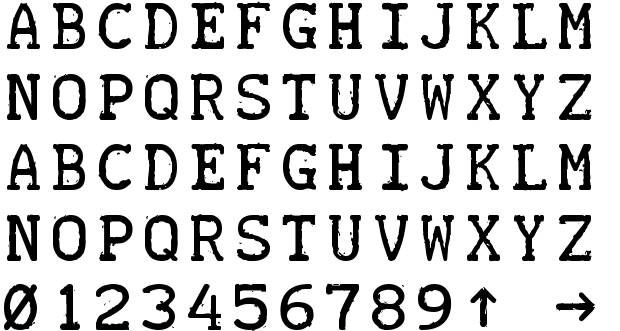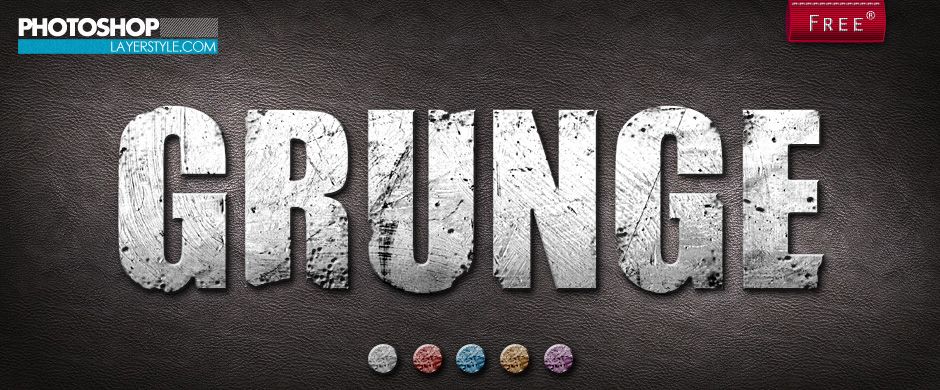
Системы компьютерной графики. Растровая графика. Adobe photoshop. Работа с текстом (модуль 5)
Системы компьютерной графики
Растровая графика
Adobe Photoshop
Работа с текстом
Модуль 5
О чем пойдет речь
Общие сведения.
Создание текста.
Форматирование текста.
Стили текста.
Текст-маска.
Текстовые эффекты.
Общие
сведения
Общие сведения
• Слово шрифт (font) сохранилось еще со времен типографской печати.
• Шрифт включает в себя:
гарнитуру,
размер (кегль),
начертание символов
• Гарнитура (typeface) – набор букв, цифр, символов и знаков препинания
одинаково рисунка.
• Семейство гарнитур (type family) объединяют гарнитуры со специфическими
свойствами.
Семейства гарнитур
Наиболее распространенные семейства:
– Serif
– гарнитура обыкновенная (с засечками).
– Sans-Serif
– рубленная гарнитура (без засечек.)
– Monospaced
– моноширинный, все символы имеют одинаковую ширину.
– Script
– рукописный, гарнитура напоминает рукописный текст.
– Decorative
– декоративный, гарнитура со специальными декоративными
свойствами в виде точек, штрихов и других украшений.
Начертания
Шрифты могут иметь разные начертания (forms).
Начертание определяется:
– насыщенностью
(weight) шрифта
светлый прямой (roman, normal),
полужирный [жирный] (bold)
– шириной (width) шрифта
сжатый (condensed) – шрифт, ширина которого меньше, чем у нормального
аналога,
растянутый (expanded, extended) – шрифт, ширина которого больше, чем у
нормального аналога,
– наклоном шрифта
курсив (italic) – начертание исторически происходит от рукописных текстов,
наклонный (oblique) – более жесткий вариант по сравнению с курсивом.
Размер шрифта определяет высоту символов. Часто используемая единица
измерения – пункт. Один пункт равен 0,35 мм.
Создание
текста
Инструментарий
Графический текст создается с помощью
инструмента Type (Текст) (клавиша T).
Существует два вида этого инструмента:
a. Обычный текст – используется для
добавления надписей в изображение.
a
b. Текст-маска – используется для
b
создания выделений в форме текста.
Если вам необходимо добавить
большое количество текста, в этом
случае удобно пользоваться буфером
обмена для переноса напечатанного
текста из любого текстового
редактора.
Особенности
Текст в Adobe Photoshop это векторное изображение.
В связи с этим есть ряд особенностей работы с ним:
Во-первых, выделять, редактировать текст легко и делается это так, как,
например, в MS Word.
Во-вторых, текст вводится автоматически на новый слой.
В-третьих, если вы захотите применить к тексту фильтры, то надо быть готовыми к
тому, что программа запросит вас разрешение на растрирование этого слоя. А
после растрирования вы должны помнить, что теперь текст ведет себя как
обычное растровое изображение.
Создание текста. Первый способ
1.
Выберите инструмент Type (Текст) (клавиша T)
для горизонтального или вертикального текста.
2.
Щелкните инструментом на изображении –
активизируется указатель ввода текста.
Автоматически появится новый слой.
3.
На панели свойств сделайте нужные настройки
для текста.
4.
Введите нужный текст.
5.
Для завершения процедуры ввода текста на
панели свойств нажмите галочку – Commit any
current edits (b)
В случае, если вы ошибочно начали ввод текста
вам необходимо воспользоваться на панели
свойств кнопкой перечеркнутого круга –
Cancel any current edits (a)
a b
Создание текста. Второй способ
1.
Выберите инструмент Type (Текст) (клавиша T)
для горизонтального или вертикального текста.
2.
На панели свойств сделайте нужные настройки
для текста.
3.
Постройте текущим инструментом
прямоугольную маркерную рамку.
Автоматически появится новый слой.
3.
Введите нужный текст.
Он будет вводится в пределах построенной
прямоугольной рамки.
4.
Для завершения процедуры ввода текста на
панели свойств нажмите галочку – Commit any
current edits (b)
В случае, если вы ошибочно начали ввод
текста вам необходимо воспользоваться на
панели свойств кнопкой перечеркнутого круга –
Cancel any current edits (a)
a b
Отличия
Текст введен первым способом
Текст введен вторым способом
• При вводе текста
вторым способом мы
имеем возможность
регулировать область
расположения текста
с помощью маркерной
рамки, автоматически
появляющейся у
выделенного текста
(см.
рисунок снизу).
Создание текста. Третий способ
Рис. 1
1.
Постройте векторный контур нужной формы
(см. здесь).
2.
Выберите инструмент Type (Текст) (клавиша T) для
горизонтального или вертикального текста.
3.
На панели свойств сделайте нужные настройки для
текста.
4.
Установите курсор в нужное место возле контура пока
курсор не приобретет вид как на рис. 1.
Автоматически появится новый слой.
5.
Введите нужный текст.
Он будет располагаться вдоль векторного контура.
6.
Для завершения процедуры ввода текста на панели
свойств нажмите галочку – Commit any current edits
(b)
В случае, если вы ошибочно начали ввод текста вам
необходимо воспользоваться на панели свойств
кнопкой перечеркнутого круга –
Cancel any current edits (a)
a b
Полезно помнить!
• При вводе текста его
положение можно менять не
закончив операцию ввода
текста.
• Для этого переместите курсор
чуть ниже текста пока он не
приобретет вид как на рисунке
и смело перемещайте текст в
нужное место на изображении
(при нажатой левой клавише
мыши).
Панель «Глифы»
Источник: https://helpx.adobe.com/ru/photoshop/using/glyph-panel.html
Форматирование
текста
Форматирование текста
• Форматировать текст можно как до его ввода, так и после.
• При форматирование текста после его ввода следует помнить, что введенный
текст необходимо для начала выделить, иначе настройки не применятся.
• Выделять символы текста следует при активном инструменте Type (Текст).
• Настройки для форматирования текста можно найти в нескольких местах:
на панели свойств и
на дополнительных палитрах.
Настройки текста. Панель свойств
Изменение
НАПРАВЛЕНИЕ
ТЕКСТА
Определяет
ВЫРАВНИВАНИЕ
строк абзаца
Определяет РАЗМЕР
СИМВОЛОВ (КЕГЛЬ)
ВЫБОР
ГАРНИТУРЫ требуемого набора
символов
Выбор НАЧЕРТАНИЯ –
определяет
насыщенность и объем
Определяет СГЛАЖИВАНИЕ
символов текста, т.е.
позволяет сглаживать
зубцеобразные края текста
Выбор
ЦВЕТА
символов
текста
Получение
ДОПОЛНИТЕЛЬНЫЕ
ПАЛИТРЫ НАСТРОЕК
ТЕКСТА
ИСКАЖЕНИЕ
ТЕКСТА –
позволяет
расположить
текст в
векторной
рамке
произвольной
формы
ОТМЕНА
ВВОДА
текста
ПОДТВЕРЖДЕНИЕ
ВВОДА текста
Дополнительные палитры настройки текста
Настройки символов текста
Выбор гарнитуры
Размер символов текста
Кернинг – расстояние как между
отдельными символами
Задает коэффициент масштабирования
символов по высоте
Задает смещение
базовой линии текста
Выбор начертания
Интерлиньяж – вертикальное
расстояние между строками текста
Трекинг –расстояние как между
словами, так и символами
Задает коэффициент масштабирования
символов по ширине
Выбор цвета символов текста
Выбор начертания
Определяет словарь
для переносов
Определяет вид
сглаживания
Настройки абзацев текста
Выбор способа выравнивания
строк абзаца
Отступ абзаца слева
Отступ абзаца справа
Величина абзацного отступа
Интервал перед абзацем
Включение переносов
Интервал после абзаца
Палитра Properties (Параметров)
Настройки текста
Расширенные настройки текста для
шрифтов OpenType
Получение
ДОПОЛНИТЕЛЬНЫХ ПАЛИТР
НАСТРОЕК СИМВОЛОВ
ТЕКСТА И АБЗАЦА
Работа со шрифтами
Поиск шрифтов
Для поиска шрифта достаточно ввести
несколько букв его названия в окно
выбора, Photoshop отобразит все
шрифты, имеющие в названии эту
комбинацию букв.
Также для поиска можно использовать
фильтр (см. рис. справа).
Предварительный просмотр
шрифтов
Есть возможность удобно
посмотреть, как будет смотреться
тот или иной шрифт в документе.
Сделав активный текстовый слой,
открыть список и перемещать
курсор по списку без нажатия на
клавишу мыши. Шрифт в
документе при этом не меняется
пока вы не выберите нужный вам
шрифт
Работа со шрифтами из Typekit
Подробнее читайте здесь: https://helpx.adobe.com/ru/photoshop/using/fonts-typekit.html
Новинка: Переменные шрифты OpenType
• Шрифт OpenType
поддерживает такие
настраиваемые
атрибуты, как толщина,
ширина, наклон,
оптический размер и т. д.
• Photoshop поставляется с
несколькими переменными
шрифтами, для которых можно
регулировать толщину, ширину
и наклон с помощью
стандартных ползунков на
панели «Свойства».
• На панели «Символ» или
панели «Параметры» введите
поисковый запрос
«переменный» в списке
шрифтов для поиска
переменных шрифтов.
Также
можно щелкнуть значок рядом
с именем шрифта.
Источник: https://helpx.adobe.com/ru/photoshop/using/fonts.html
Команды работы с текстом
Растрирование текстовых слоев
Первый способ
Растрирование текстовых слоев
Второй способ
Важно!
Вид макета на
другом ПК –
шрифты не
растрированы,
на ПК нет
нужных шрифтов
Макет на
вашем ПК
http://manjuna.com/tutorial-web-design/
Перед просмотре изображения на другом ПК полезно текстовые слои растрировать, оставляя у
себя вариант в векторе, чтобы оставить возможность дальнейшего редактирования.
Это делается для того, чтобы в случае, если на другом ПК не загружены нужные шрифты
дизайн-макет отображался корректно.
В случае, если текст будет оставаться в векторном представлении, а на ПК не будут загружены
нужные шрифты при открытии документа программа выдаст предупреждения и загрузить текст
с другими шрифтами. Это может привести к некорректному отображению дизайна.
Автоматическая вставка текстовых заглушек
Задание. Создание портрета из текста
Создать портрет из текста.
портрет.jpg
До
После
Задание. Создание портрета из текста
1.
2.
1
Открыть портрет, на основе которого сделаем портрет из
текста (portrait.jpg).
Построить выделение портрета с помощью команды Color
Range (Select/Color Range).
4
5 Select/Color Range
6
2
10
7
3
8
9
3.
4.
Создать новый слой (Layer 1) и залить выделение черным
цветом.
Снять выделение.
Задание. Создание портрета из текста
5.
6.
Создать текстовую заглушку размером с документ
(см. рис. слева).
Загрузить выделение (Ctrl + кликнуть по миниатюрке
слоя Layer 1) (см. рис. Справа).
Задание. Создание портрета из текста
7.
8.
9.
Создать маску слоя с текстовой заглушкой (см. рис.
слева).
Снять выделение.
Создать новый слой (Layer 2) под текстовым слоем и
залить его белым цветом.
(см. рис. справа).
Задание. Создание портрета из текста
8. Сравните результат.
Стили
текста
Зачем нужны стили текста?
• Для соблюдения текстового единообразия в
подготовки изображений одного проекта, при работе с
большим количеством текстовых слоев и др. можно
автоматизировать работу, используя стили текста.
• Различают стили символов и стили абзацев.
Стили символов
Стиль символа включает в себя атрибуты форматирования
символов к символам, абзацу или даже к нескольким абзацам.
Можно создать стили символа, а затем применить их позднее.
Выберите Window > Character Styles, чтобы открыть палитру
«Стили символов». Чтобы применить стиль символа, выделите
текст или текстовый слой и щелкните стиль символа.
Стили шрифтов являются иерархическими: параметры, указанные
вручную, переопределяют любые примененные стили символов,
которые в свою очередь заменяют примененные стили абзацев.
Этот иерархический подход объединяет эффективность
использования стилей и гибкость при настройке проектов.
Подробнее изучить:
• Создание стиля символа.
• Редактирование стиля символа.
• Определение стилей шрифтов по умолчанию.
См. здесь: https://helpx.adobe.com/ru/photoshop/using/formatting-characters.html#main-pars_header_3
Стили абзаца и символов
Стиль абзаца включает в себя атрибуты форматирования как
символов, так и абзацев и может быть применен к одному или
нескольким абзацам. Можно создать стили абзаца и затем
применить их позже.
Выберите Window > Pharagraph Styles, чтобы открыть палитру
«Стили абзацев». По умолчанию каждый вновь созданный
документ содержит стиль «Основной абзац», который
автоматически применяется к вводимому тексту. Этот стиль
можно изменить, но переименовать или удалить нельзя. Стили,
созданные пользователем, можно переименовывать и удалять.
Можно также выбрать другой стиль в качестве стиля,
применяемого к тексту по умолчанию.
Чтобы применить стиль абзаца, выделите текст или текстовый
слой и щелкните стиль абзаца.
Стили шрифтов являются иерархическими: параметры, указанные
вручную, переопределяют любые примененные стили символов,
которые в свою очередь заменяют примененные стили абзацев.
Этот иерархический подход объединяет эффективность
использования стилей и гибкость при настройке проектов.
Редактирование стилей абзаца
Двойной клик
Подробнее изучить: https://helpx.adobe.com/ru/photoshop/using/formatting-paragraphs.html#main-pars_header
Важно!
• При создании нового документа для
проекта начинайте с создания стилей для
символов и абзацев текста.
• Например, полезно задавать стили для:
–
Заголовков.
Подзаголовков.
Основного текста.
Подписей.
Гиперссылок.
И т.п.
Текст-маска
Работа по созданию и форматированию текста-маски
идентична работе с обычным текстом.
Пример
1.
2.
3.
4.
Выберите инструмент Horizontal
Type Mask.
Настройте параметры текста:
кегль (размер) – 160рt
шрифт – Verdana
начертание – Bold
Кликните на изображении и
введите слово «Фрукты»
заглавными буквами (должно
получиться как на верхнем
рисунке).
Завершите ввод текста Commit
any current edits.
Получатся выделения в форме
букв (см. средний рисунок)
Этот инструмент хорошо использовать
для создания маски слоя (см. нижний
рисунок), для вырезания изображения в
виде букв текста и т.п.
Текстовые
эффекты
Текстовые эффекты
Текстовых эффектов можно добиться с помощью:
1. Применения к тексту настроек форматирования.
2. Применения к слою с текстом эффекта слоя.
3. Применения к слою с текстом фильтров.
Применение настроек форматирования
Буквица
Это будет не буквица как таковая, а ее имитация.
В этом случае достаточно увеличить первую букву в слове
В случае, если вы хотите сделать не имитацию, а настоящую буквицу, то
увеличить букву мало, следует сместить положение ее базовой линии
вниз
«Пляшущий» текст
В этом случае последовательно выделяя каждую букву слова, измените
ей смещение по базовой линии текста: для первой буквы сделайте
положительное смещение, для следующей – отрицательное и т.
д.
Фигурный текст
В этом случае, воспользуйтесь с панели свойств инструментом
искажения текста, который позволит вам расположить текст в векторной
рамке произвольной формы. Например, сделать слово «рыба» в форме
рыбы и т.п.
Вы можете, экспериментируя, продолжить этот список и прислать
преподавателю, как дополнительный бонус к домашнему заданию
Применение эффекта слоя для текстовых эффектов
Чтобы получить представление каким образом создаются
текстовые эффекты с помощью эффектов слоя проделайте
урок «Отливаем текст из золота в Фотошоп»:
https://photoshop-master.ru/lessons/text/otlivaem-tekst-iz-zolota-v-fotoshop.html
Применение фильтров для текстовых эффектов
Однако, на практике редко используют только фильтры или
только эффекты слоя, поэтому часто для достижения
разнообразных текстовых «красивостей» применяют
комбинацию всех возможных способов создания текстовых
эффектов.
Проделайте еще один урок по созданию золотых букв, в котором
эффект достигается уже не только эффектами слоя, но и
фильтрами.
Урок «Пишем золотыми буквами в Фотошоп»:
https://photoshop-master.ru/lessons/text/pishem-zolotyimi-bukvami-v-fotoshop.html?download=e59522068f3f0aec4d537d579556ec02
Задание
• Возьмите любое изображение.
• Повторите все имеющиеся на данном примере текстовые
эффекты данного плаката.
Обязательно к изучению!
• В приложениях к модулю 5 вы расширите свои знания
по работе со стилями слоев и фильтрами.
Спасибо
за внимание!
Твои вопросы?
Ты можешь их задать:
На форуме «Вопросы по курсу»
56
Ликбез онлайн-версии фотошопа. Шрифты и изготовление быстрой визитки
Этот мастер-класс в помощь тем, кто не умеет работать в фотошопах и аналогичных программах. Или имеет только поверхостное ознакомление с ними. Мы разберем все инструменты онлайн-версии фотошопа, которую не нужно ни скачивать, ни устанавливать. Расскажу, где искать и как устанавливать красивые русскоязычные шрифты. Я открою пару интересных секретов быстрой обработки изображения.
И расскажу, как быстро сделать визитку и подготовить ее к печати дома.
Я заметила, что на Ярмарке Мастеров очень много мастеров, не имеющих опыта работы в фотошопе. Программа дорогая, не все могут ее себе позволить. Кроме цены – она также весьма сложная и разобраться без специальных мастер-классов в ней тяжело. Хочу немного помочь всем тем, кому нужно делать бирочки, визиточки, баннеры или просто подпись к фотографии – это легко и просто делается без скачивания спец-программ. Мы будем использовать так называемый фотошоп-онлайн. Внимание! Нам нужен будет фотошоп с такой заставкой вначале:
Нашли? Отлично! Пока мы не начали работать – давайте подберем какие-нибудь интересные шрифты! Именно подбор шрифтов – главная проблема для многих. Во-первых, где их брать? Во-вторых – как устанавливать? Все очень просто. Шрифты находятся в интернете. В поисковик забиваем «шрифты скачать». Сайтов очень много. Как выбрать среди них?
Критерии первый: должна быть возможность как-то выбрать просмотр только кириллических или русских шрифтов.
Везде их называют по-разному. Суть в том, чтобы нам показали максимальный выбор шрифтов с русской раскладкой. Конечно, это актуально в том случае, если визитки, бирочки или баннер вы хотите заполнять на русском языке. Если вам нужны латинские шрифты – все просто. Качать можно любой понравившийся – 90% шрифтов именно англоязычные.
Вы смогли отрегулировать фильтр поиска или же там просто русские шрифты выделены отдельной категорией. Заходим. Вы увидите название шрифтов, под ним картинка – название шрифта, написанное самим шрифтом. Шрифтов сотни и тысячи. Не стоит пытаться скачать все. Выбирайте те, что нравятся. Безусловно, всегда полезны рукописные; “bold”, т.е. жирные; различные “old”, т.е. под старину; готические и прочие. Часто, принадлежность к какой-либо категории у шрифта написана в названии. Вы часто можете увидеть один и тот же шрифт, который сначала идет отдельно bold, потом italic (курсив), затем bold italic. Почему так? Ведь мы привыкли, что выбираешь шрифт, а потом отдельной кнопкой делаешь его жирным, курсивом или прочее.
У нестандартных шрифтов такой возможности нет. Если шрифт состоит из тонких букв – таким он и останется. И толстые буквы будут только, если вы скачаете отдельный такой же шрифт с подписью bold. Есть еще варианты, когда буквы прозрачные, т.е. есть только их контур, или же заполнены некоторым узором, а не просто черные. В общем, полистайте, посмотрите – это ужасно интересно. Руки так и тянутся все скачать 🙂
Теперь второй критерий: возможность посмотреть шрифт до скачивания! Обычно есть кнопка «посмотреть шрифт» или «весь шрифт». Или при нажатии на шрифт – он открывается в окне и там будет его раскладка. Выглядит это так:
Зачем это нужно? Дело в том, что, даже когда вы выбираете только кириллические или русские шрифты… все равно среди них как минимум половина будет без русской раскладки! Теперь как разобраться в таблице букв. Сначала идут латинские буквы – большие и маленькие. Потом цифры, затем значки… и только после этого идет русская раскладка – также больших и маленьких букв.
Если на русской раскладке вместо букв пустые окошки или черные квадратики – у этого шрифта нет русской раскладки! Бывает, что у шрифта есть только большие или только маленькие буквы. Конечно, лучше всего, если присутствуют все буквы – и большие, и маленькие. Но это не обязательно. Наличие знаков – тоже желательно. Хотя бы та же @ — нужна нам для того, чтобы написать в визитке почту. Но, если шрифт вам очень нравится, а «собачки» там нет – не расстраивайтесь – найдете этот значок в другом шрифте, хотя бы в том же стандартном.
И так. Шрифты накачали. Установить их очень просто. Если у вас старая версия оперативной системы, то Мой компьютер-Windows-Fonts. Распаковываем шрифты из архива, если они были в архиве. Переносив шрифты туда без папок! Прямо в корень. Он их начнет устанавливать после этого сам. Если у вас новая оперативная система (хотя бы семерка) – тогда просто щелкните два раза на каждой файле шрифта – и он начнет устанавливаться сам. Шрифты тогда появятся у вас в ворде, фотошопе и также онлайн его версии (все программы желательно открыть заново после установки шрифтов).
Теперь можно приступать к изучению фотошопа-онлайн.
Сначала ликбез. Разберем окно, которое открывается при старте.
1. Создать новый рисунок. При открытии появляется окно. Первая строка — «имя» — можно не вводить. Затем — «предварительные настройки» — тут есть некоторое количество стандартных форматов, которые можно выбрать. Если вы не хотите стандартный размер изображения – выбираете его сами, выставив ширину и высоту ниже. К сожалению, выбор только в пикселях, разрешение выставлять нельзя! Если хотите разрешение побольше – лучше найти как-то файл с изображением в интернете и открыть его в фотошопе. Какая картинка не важна – сверху нарисовать можно что угодно) Главное, получить файл с изначально высоким разрешением.
2. Загрузить изображение с компьютера. Тут все понятно. Кушает он достаточно много форматов, в том числе, и psd – формат, сохраняющий слои.
3. Можно открыть файл сразу из интернета.
Когда нашли в интернете понравившуюся картинку, ее можно не скачивать, а нажать правую кнопку мыши и выбрать «копировать адрес изображения».
4. Открыть изображение из библиотеки – т.е. из всяких соцсетей.
5. Последнее – открыть с телефона.
Мы создали или открыли файл. У нас есть горизонтальные вкладки и вертикально расположенные окна инструментов.
Горизонтальное меню (сверху):
Файл: понятно — тут открываем, сохраняем и прочее.
Редактировать: тут инструменты для выделения, поворота, копирования и вставки. В какой-то степени, они дублируют основные инструменты, которые находятся на вертикальной панели слева. Редактирование – Free transport – это возможность повернуть или отразить рисунок, а также уменьшить. Действует только на слой! Чтобы пропорции изображения не менялись – зажмите shift. Чтобы отразить рисунок – зажмите правую кнопку на уголке и переместите ее слева направо, чтобы отразить горизонтально и сверху вниз, чтобы вертикально.
Только shift не зажимайте. Если зажать shift – изображение повернется, будто вы его просто повернули верх ногами 🙂
Изображение: тут можно переворачивать наш файл. Именно файл! Файл состоит из нескольких слоев – переворачиваться будут все слои. Тут же есть отразить по вертикали или горизонтали, также можно менять размер файла.
Слои: меню по работе со слоями. Почти все, что там есть – дублируется другими инструментами.
Коррекция и фильтр: обработка фотографий. Свет, яркость, цветность, различные деформации, формы и прочее. Честно говоря, там надо каждому самому покопаться. Вместить сюда курс коррекции фотографии и использования фильтров… лучше отдельным постом, хотя тут и так постов на эту тему много. Тут есть даже такие фильтры… которых в фотошопе нет! Например, калейдоскоп 🙂 А еще есть инструмент «придание точечного стиля» – из любого рисунка можно сделать схему для вышивки!
Просмотр: тут есть возможность открывать разные окна, которые очень нужны.
Окна горизонтальных дополнительных инструментов, навигатор (чтобы приближать), слои (те самые!), журнал (она же история, чтобы можно было вернуться назад – ужасно полезно! Журнал свой для каждого открытого файла.
Язык и помощь – тут тоже все ясно 🙂
Рассмотрим левое вертикальное окно. Условно инструменты можно поделить на инструменты для выделения, рисования и коррекции. Рассмотрим первый блок.
Когда вы жмете на одну из кнопок инструмента – в горизонтальном окне сверху появляются доп. функции (на сером фоне).
Обрезка – инструмент, позволяющий не только обрезать, но и контролировать размер обрезки края. Тут все ясно – тыкаем на инструмент, обрезаем картинку по краю, например. Если сверху на серой полосе у нас стоит в окне «без ограничений» — то можно просто обрезать изображение так, как хочется. Если нам нужно сохранить соотношение сторон (по соотношению сторон открытого файла) – например, для того, чтобы потом напечатать фотографию для альбома – то вбираем «соотношение сторон».
По умолчанию стоит 1:1 – т.е. с сохранение пропорций сторон. Если нам нужно задать какой-то определенный размер, то выбираем «выходной размер», ставим нужное количество пикселей по вертикали или горизонтали. Это удобно, например, для создания аватарок. Выставлять все параметры нужно до того, как вы начали обрезку файла!
Выделение – все логично. Что-то выделяем, затем, чтобы переместить выделение, не вырезая картинку, просто жмем на выделенный участок, а чтобы вырезать и использовать выделенное где-то еще, его можно перетащить с помощью инструмента «перемещение». Пробежимся по дополнительным функциям. Значит, два вида выделения: прямоугольное или в форме эллипса. Ограничение – тоже, что в инструменте «обрезка». Растушевывание – это возможность сделать край при выделении не резким, а растушеванным. Эффект от инструмента «в форме эллипса» показан на первой картинке, а от инструмента «прямоугольное выделение» на второй картинке. Здесь края прямоугольника за счет растушевывания можно красиво сгладить.
На примере размер растушевывания =17. Но это все зависит от начального разрешения файла.
Перемещение – нужен в работе со слоями, о которых я расскажу позже. С помощью него можно перемещать объект на слое по нашей картинке и перемещать слои в других файлы.
Лассо – это также инструмент выделения, но более тонкого, чем простое выделение. На мой взгляд свободное лассо вообще бесполезно. Гораздо удобнее многоугольное лассо. С помощью него можно очень точно выделить любой объект. Чтобы край был не резкий, можно даже немного растушевать. Чтобы вырезать объект, сначала его приближаем (инструмент «навигатор» справа). Затем левой кнопкой мыши идем вдоль края, отмечая как бы точки перегиба лассо там, где наша линия меняет направление. Этот же инструмент есть и в нормальном фотошопе. Там им пользоваться очень удобно, а вот в онлайн-версии много глюков. Во-первых, чтобы удобнее вырезать по линии объект – его нужно приблизить, а, значит, объект не влезет весь на экран и его нужно передвигать.
А в онлайн версии сдвинуть окно нельзя во время выделения. Точнее можно, но, почему-то, выделенная вами область тут же смещается вслед за окном. Короче, неудобно! Ниже, в МК по созданию визитки я поподробнее расскажу, как вырезать, также используя дополнительно инструмент «волшебная палочка».
Волшебная палочка – это автоматическое лассо. Не пользуйтесь этим инструментом, если хотите аккуратный результат. Пользовать им можно только на очень контрастных изображениях. Хорошо на черно-белых. Но граница все равно будет неровной. Это убыстряет процесс, но только если нет градиента цветов – а он есть почти всегда. Использовать ее можно только в комплексе с другими инструментами выделения. Внизу, на мастер-классе визитки я это покажу.
Второй блок инструментов:
Карандаш и кисть – инструменты рисования. Честно говоря, эти инструменты чаще используют те, у кого есть планшет и те, кто умеет рисовать. Это особенно относится к карандашу.
Не понимаю, что с ним делать. А вот «кисть» очень полезный инструмент. Заходим в меню кистей.
Сверху появляется дополнительные иконки – чтобы открыть меню выбора кистей нужно нажать на изображение кисти рядом со словом «кисть:». Там вы видите стандартный набор кистей. Можно достаточно интересным методом создать свою кисть – выбрать круглой она будет или квадратной, какой нажим, где разрезы в контуре и прочее. Но давайте научимся использовать уже готовые кисти.
Кроме стандартного набора тут есть некоторый набор, который можно загрузить из архива программы. Нажимаем кнопку «другие параметры». Там потыкайтесь – есть штук 20 разных наборов кистей, вполне даже приличных. Чтобы они добавились – жмем добавить. Для меня оказалось абсолютной неожиданностью, что функция загрузить кисти с компьютера тут есть… вот только стандартный тип файла кистей .abr он не видит. И требует какой-то непонятный .pbr! Что за невидаль? Сунулась в интернет. Все кисти только в формате .abr! И люди, задающих один и тот же вопрос – где взять кисти в странном формате .
pbr? Попробовала взять кисти из своего нормального фотошопа и сохранить в странном формате, но фотошоп отказался. Интернет ищет только кисти формата .abr. Это ужасно печально, так как выбор стандартных кистей из тех, что он подгружает из своего архива, невелик. Нет красивых завитушек, мало растительного орнамента… Ну, что поделать. Но, если вы используйете фотошоп или его бесплатный аналог, то использовать кисти нужно. Для этого – вводим в поисковик «кисти для фотошопа». Обычно рядом с кистями есть и инструкция по их установке. Для каждой программы по-разному.
Ладно, вернемся к другим функциям кистей. Вот вы загрузили разные кисти из архива. Можно менять их размер. Делать кисть прозрачнее. Есть также функции Hard tip – т.е. резкий край, диффузия – рассеивает узор кисти. А инструмент «рассеять» – актуален только если вы хотите изобразить летящие листья или рассеянные звезды. Т.е. жмешь несколько раз – а листья появляются не в том месте, где нажимаешь, а в случайном месте. В большом открывающемся меню еще есть три параметра – диаметр, регуляция той самой рассеивания – расстояния между рассеянными объектами и твердость.
Ластик – тут все ясно. Можно стирать уже нарисованное. Удобно, что ластик действует на слой. Т.е. можно нарисовать что-то на отдельном слое – и, если потребуется стирать, стирать будем на отдельном слое. Я постаралась показать. На мишку я наложила другой слой и легко смогла с него стирать, не затрагивая мишку. Также можно и рисовать. Кстати, край ластика тоже можно рассеивать. Формы ластика – это те же формы, которые мы загружали в кисти.
Заливка – ну… это возможность заливать что-то цветом. Честно говоря, удобна только для заливки основного фона. Действует на слой.
Градиент – это та же заливка, только красивым градиентом. Инструмент работает так: левой кнопкой мыши отмечаем начальную точку, не отпуская кнопку, тянем в одну из сторон – чем дольше тянем – тем более растянутый будет градиент. Можно тянуть по горизонтали, можно по диагонали. Есть стандартные градиенты, можно создать самому. Для этого на горизонтальной шкале градиента нажмите в любом месте – появится зарубка.
Каждую такую зарубку можно двигать, менять ее цветность и непрозрачность. Там же можно делать линейный градиент, радиальный, с повторами и прочее… Активная зарубка обозначена черным треугольником сверху. Я ее отметила красным. Я убрала прозрачность – и в этом месте градиента стал виден нижний слой с мишкой.
Штамп – очень интересный инструмент коррекции. Наведите курсор на то место, которое хотите «запомнить», нажмите ctrl – курсор поменяет форму на крест – и нажмите левую кнопку мыши. Чтобы текстуры лучше ложились в новое место – лучше использовать кисть с растушеванным краем. Затем переносите объект в другое место. Таким нехитрым инструментом я сделала мишке лишний десяток глаз… Но чаще всего инструмент применяют для коррекции дефектов кожи или же обрезанного края, который нужно дорисовать.
Рисование – это инструмент рисования прямоугольников, кругов и линий. Опять же можно сделать их прозрачными, можно добавить границу. Внутренняя часть фигуры будет заполнена тем цветом, что указан в горизонтальном меню справа, а цвет границы, если ее поставить хотя в 1 пикель, цветом, который указан слева внизу.
Дальше идут инструменты важные скорее для обработки фотографий.
Размытие и резкость – тут все ясно. Делаем что-то размытым или резким. Причем можно регулировать интенсивность и форму кисти.
Палец и губка – это странные инструменты. Некоторые люди используют палец для размытия дефектов. Губка – это что-то странное. Представьте, что у вас есть рисунок акварелью – и вы на него капнули водой и начали по нему возить губкой. Вот что-то такое…
Осветление и затемнение – все для работы с фотографиями.
Красные глаза – понятно, убирает красные глаза.
Точечная коррекция – это интересные инструмент для редактирования фотографий. Убрать родинку или прыщик? Нажали и готово! Даже лучше пальца) Штамп – это примерно тоже самое, но коррекция более автоматически сливает текстуры. А штамп просто накладывает изображение сверху.
Раздувание и дисторсия – это такое веселый инструмент, которым можно делать смешные рожицы с большими глазами или подправлять фигуру 🙂
Пипетка очень полезна – наводите на нужный цвет – и вот он в палитре…
А – это текст.
Как раз тут множество шрифтов, которые мы себе установили. Можно менять размер, можно менять жирность (это называется стиль), курсив и прочее (в других редакторах так нельзя, только тут уже жирный шрифт можно сделать еще жирнее, а курсив… еще более наклонным :)), поменять цвет. Шрифт выбираем из тех, что установили себе на компьютер – программа использует шрифты с вашего компьютера. Шрифт всегда печатается на новом прозрачном (!!!) слое. Так что вы легко сделаете подпись к вашей фотографии.
Палитра! Тут не все так просто. Она тут аж в 4-х варианта. HSL, RGB, WEB и IMG.
IMG – это фактически не палитра. При открытии файла – программа считывает все цвета, которые в ней есть и отражает их.
WEB – это стандартная палитра, закомая вам по ворду. Она достаточно ограничена в цветах.
RGB – тут вы видите три круга с пересечением. Внизу линии – они меняют цветность каждого круга. От этого меняется цвет в центре пересечения трех кругов.
HSL – тут немного сложнее. Верхняя горизонтальная линия двигает кружок по цветовой окружности. Средняя – отвечает за интенсивность от белого до яркого цвета, нижняя – тоже от черного до яркого цвета. За счет этих двух линий кружок бегает по ромбу внутри окружности. Кроме того, за счет линейки дополнительных цветов в палитре справа можно к любому выбранному цвету сразу увидеть несколько близких тонов. Еще интересно. У каждого цвета есть свой номер. Это в том случае, когда вам нужно точно сохранить оттенок – можно просто ввести его номер.
Теперь о слоях. Это самое важное в фотошопе.
Если вы когда-то открывали Paint, то заметили, что там ты рисуешь всегда на одном и том же слое. Если что-то нарисовал – там оно и остается – ни сдвинуть, ни стереть, не повредив другую часть рисунка. А вот в фотошопах и его аналогах можно. Слой можно представить себе прозрачной пленкой. Вы можете нарисовать на каждом слое пленки разное, а потом легко двигать их между собой, при этом общая картина будет меняться.
При этом слой можно сделать невидимым, если он вдруг вам мешает прямо сейчас. Слои можно менять местами. Всегда создавайте новый слой, когда собираетесь что-то рисовать. Когда создаете текст – слой создается автоматически, называется текстовым и отмечен буквой «А» в меню слоев. На текстовом слое нельзя рисовать, редактировать его можно ограниченно. Зато можно менять в любой момент шрифт и его цвет. Текстовый слой можно растрировать – т.е. превратить в растровый. Тогда менять шрифт уже будет нельзя, буквы на слое будут простым изображением, как и любой другой рисунок. Зато можно уже его редактировать всеми инструментами программы. Далее… не забывайте! Если вы рисуете что-то сами кистью – обязательно создавайте новый слой. Так как именно на слой направлено действие всех инструментов фотошопа. Если вы нарисуете что-то просто на слое с изображением и захотите потом что-нибудь стереть – не получится. Новая часть рисунка будет стираться вместе с изображением.
Как создать слой?
Красной стрелкой я отметила кнопочку.
Новый слой будет виден в меню справа весь в серо-черных квадратиках, что означает, что он прозрачный. Галочка напротив слоя означает, что сейчас он видимый. Убираем галочку – и слой становится невидимым, хотя он и есть). Если зажать кнопкой слой и поднести к ведерку (справа от кнопки создания нового слоя) – слой будет удален. А если к кнопке создания нового слоя – слой будет скопирован.
Самая левая кнопка (обвела красным) – регуляция прозрачности и режим соединения слоев. Тут даже не сразу объяснишь, что это. Прозрачность – это понятно. А вот режим? Если на пальцах – нижний слой, как бы подложка. Режим можно применять только к слою, находящемуся над каким-либо слоем слоем. И он будет по-разному взаимодействовать с нижним слоем. Поменяете нижний слой – картина изменится. Вот примеры (верхний слой буквы, нижний слой мишка):
Это надпись сделана коричневым цветом, затем к ней применены некоторые режимы. Если это не надпись, а какое-то изображение – тут можно очень интересно поиграть.
Тату сделать на плечо, синяк под глазом! Шутка-шутка 🙂 Также у нас есть еще интересная кнопка – стили слоя. Это третья кнопка слева (обвела красным). Вот как можно с помощью этих инструментов оформить текст: Тень снаружи, Тень внутри букв, Добавление объема и текстуры буквам, Свечение снаружи, Свечение внутри букв. В каждом инструменте там есть еще дополнительные функции – куда направить тень, насколько она интенсивная, насколько размыта и прочее.
Еще один важный момент. Любой открытый файл (если он не psd или tiff) в фотошопе будет отображаться как один слой с замочком. Замок – значит закрытый. Его нельзя ни двигать, ни редактировать. Просто щелкните два раза на замочке – и он сменится на галочку. Все – теперь с этим слоем можно делать что угодно. Слои можно передвигать – ведь от того, какой слой сверху – можно получить совершенно разные эффекты.
Кажется все по инструментам. Теперь еще пару секретов.
Если у вас фото на светлом фоне, но он отнюдь не белый. Что делать? Лучше бы вырезать и вставить на белый фон, но это бывает очень трудоемко… поэтому есть секрет. Коррекция – кривые. Там жмем на пипетку с белым. Затем направляем ее на фон.
И все. Другие цвета при этом остаются сочные и яркие. Если с первого раза фон не весь стал белым – тыкаем этим же инструментом в проблемное место. Кривые вообще хороший инструмент для коррекции яркости фотографии. Он более гибкий чем просто яркость-контраст.
Теперь, допустим. Вы нашли объект… но цветовая гамма вам чуток не подходит. Бантик фиолетовый, а вам бы такой же, но желтый. Коррекция-цветовой фон/насыщенность.
Потрясающий инструмент! Он полностью меняет цветовую гамму. Плюс можно менять яркость и интенсивность выбранной гаммы. При этом черный и белый не меняются. С помощью этого же инструмента можно спасти желтые, красные и зеленые фотографии, в которых не выровнен баланс белого.
Давайте теперь сделаем визитку-пятиминутку. Печатать ее можно дома или в типографии.
Сначала нам нужно создать файл нужного размера. Но у нас задавать размер можно только в пикселях. Визитка же должна быть 9Х5 см. Поэтому скопируйте шаблон из этой темы.Его-то мы и открываем в фотошоп-онлайне. Шаблон для визитки (9Х5 см, 300 dpi) находится в моих эскизах: https://cs1.livemaster.ru/storage/9e/6a/f69147ef3efec862b9fd05585e.jpg
Теперь открываем какой-нибудь файл, который будет нашей основной картинкой. Пусть будет тот же мишка. Он на белом фоне – это удобно. Но с белым фоном каждый может. Сейчас я научу вас убирать любой фон. Ведь красивый белый фон – редкость.
Инструментом «выделение» – выделяем нужную область, инструментом «перемещение» ( курсор должен измениться на ножницы) перетаскиваем мишку в наш шаблон. Он откроется новым слоем (справа виден новый слой 1). Его можно свободно двигать.
Чтобы было лучше видно белый фон у медведя – покрасим временно основной фон визитки в черный цвет. Не забывайте постоянно проверять на каком слое вы работаете – активный слой выделен голубым.
Наш мишка весьма контрастный – поэтому можно «волшебной палочкой» убрать белый фон, на котором он сидит. Жмем волшебной палочкой на фон вокруг мишки – он выделяется, жмем delete. Правой кнопкой мыши отменяем выделение и смотрим результат. Край не радует взор – зато быстро.
Приближаем с помощью навигатора справа, активируем лассо, выбираем многоугольное лассо. И дальше по чуть-чуть начинаем красиво ровнять край. Т.е. выделяем небольшие куски и удаляем лишнее кнопкой delete.
Также я показала различие между не обработанным краем, обработанным без растушевывания и с ним.
Лучше растушевать потом самому. Делаем это инструментом «размытие». Ставим интенсивность 50 и проходимся по всему краю чуть-чуть.
Меняем цвет в палитре на белый, переключаемся на нижний слой визитки и красим его заливкой в белый.
Теперь давайте сделаем какой-нибудь текст. Инструментом «текст» пишем название. Пусть будет «Пушистый мишка». Выбираем шрифт, размер и цвет.
Сделаем буквам тень с помощью стиля слоев.
Затем я решила добавить небольшой «слоган» под названием. Я хочу, чтобы его цвет совпадал с цветом тени у букв про пушистого мишку. Беру «пипетку», тыкаю на тень – и вот у меня в палитре нужный цвет.
Пишу слоган. Мне кажется, что тут подходят какие-то небольшие буквы, прописные. Потом добавила контактные данные. В принципе, готово. Тут уже цвет и шрифт каждый подбирает по своему вкусу. Хотя, на мой взгляд бедновато получилось, зато ничего лишнего.
Но мне захотелось последний акцент сделать – добавить бантик. Переношу его из открытого файла так же, как и мишку, убираю белый фон, ровняю край. Затем использую инструмент free transport и поворачиваю его под углом.
Пусть бант будет в углу. Чтобы он не закрывал текст переношу слой с бантиком под другие слои. Для этого просто выделите слой, нажмите левой кнопкой мыши на него и тяните вниз, не отпуская левую кнопку. Затем я сделала слой с бантиком чуть менее прозрачным – а то ярко. Теперь буквы контактов в этом цвете не смотрятся – изменим. А слою «уютные игрушки» сделаем белое свечение с помощью стиля слоев.
Ммм… еще немного подправила цветовую гамму – название теперь пусть будет светло-песочный, а тень фиолетовая.
Вуаля. Визитка-пятиминутка готова! Файл – save as – сохраняйте обязательно в двух форматах. Jpeg и pxd. Pxd – аналог формата psd – он сохраняем все слои, так что вы в любой момент сможете вернуться к вашему файлу, изменить поменявшийся номер телефона или еще что-то. К тому же, можно сохранить промежуточный вариант и не бояться, что он пропадет, пока вы пойдете в магазин за хлебом. Я вот, например, делаю бирку к каждому темари абсолютно индивидуально – к каждому пишу название, вставляю фотографию, описание и хайку.
Так что файл, который можно постоянно редактировать очень-очень полезная вещь. Формат bmp – тоже полезен – он объемный, но, в отличие от jpg, качество не теряется. Еще есть tiff – это тоже формат, сохраняющий слои. Не проверяла, насколько он тут корректно работает. Но зато через него работу из онлайн-фотошопа можно перенести в другую программу, работающую с tiff. Для печати в типографии тоже, пожалуй, лучше себе tiff сохранить.
Если вы печатаете дома. Готовый файл нужно подготовить. Ведь мастер печати винды не сохраняет масштаб файла. Поэтому отрываем наш файл в формате jpg в фотошопе-онлайн. И создаем новый файл формата 2480х3508 пикселей (это формат А4 при разрешении в 300 dpi). Далее в меню слои выделяем наш слой визитки, нажимаем левую кнопку мыши и тянем слой на наш лист А4. .
Так как визитка белая – мы можем потерять ее края. Инструментом «стиль слоя» добавим светящуюся рамочку. Далее копируем слои визитки кнопкой создания нового слоя и расставляем их на листе.
Сохраните в формате jpg. Все, можно печатать. Только, желательно, использовать бумагу потолще 🙂 Хотя бы 160 г/см3.
Вот такой получился ликбез с небольшим мастер-классом. Надеюсь, кому-нибудь пригодится. Могу подобный мастер-класс по инструментам обработки фотографий сделать. Пишите свои вопросы – вдруг что-то из инструментов непонятно… или какой-то шаг нужно подробнее описать.
Интересная органическая типографика Adobe Photoshop Tutorials
psddude Ресурсы Учебники 17914 08.05.2013 7:06:55 08.05.2018 00:00:00
Я люблю текстовые эффекты, и каждый день в Интернете появляется множество новых идей. В сегодняшнем списке я собрал несколько интересных руководств по органической типографике , сделанных в Adobe Photoshop, которые вы, возможно, захотите проверить. Я попытался собрать некоторые образцы из каждой органической темы, такой как земля и трава , еда и напитки , птицы и животные и т. д. Надеюсь, вам понравится и вы решите поделиться им с друзьями.
Твит
Обычно при создании текстового эффекта вы начинаете с типа шрифта. Итак, ознакомьтесь с этим удивительным списком из более чем 25 бесплатных шрифтов Cake , которые вы можете скачать и использовать в коммерческих проектах. Используйте шрифты торта онлайн с текстовым редактором MocoFun или установите шрифты на свой компьютер и используйте их в Photoshop.
Список также включает в себя шрифты для выпечки и шрифты для кофе, которые можно использовать для создания собственных логотипов или потрясающей типографики еды.
Учебное пособие Photoshop по 3D-типографике Sweet Desert — Premium
Учебное пособие Photoshop по 3D-типографике Sweet Desert — Premium от tutsplus
Учебное пособие по типографике с мехом животных
Учебное пособие по типографике с текстурой меха животных от tutsplus
Учебное пособие по типографике с мехом животных Nature 20 0 Spring 0 Photoshop 90 Text 90 Эффект Adobe Photoshop Tutorial
Природа Весна Текстовый эффект Adobe Photoshop Tutorial by textuts
Birds and Feathers Collage Typography Photoshop Tutorial
Birds and Feathers Collage Typography Photoshop Tutorial by gomediazine
Skin Textured Typography Photoshop Tutorial
Skin Textured Typography Photoshop Tutorial by designinstruct
Organic Typography Text Effect Photoshop Tutorial — Premium
Organic Typography Text Effect Photoshop Tutorial — Premium от tutsplus
Джунгли 3D текстовая типография Photoshop Tutorial
Джунгли 3d текстовая типография Photoshop Tutorial by wegraphics
3D Природа Типография Adobe Photoshop Учебник
3D Nature Typography Adobe Photoshop Учебник от Creativefan
Typography Photoshop.
Создаем Текстовый Эффект Мясной Колбасы в Фотошопе psddude
Текстовый эффект пива Учебник Photoshop
Текстовый эффект пива Учебник Photoshop от iceflowstudios
Food Eat Typography Учебное пособие по фотошопе
Учебное пособие по фотошопе пищи с помощью фотошопа от Fanextra
Ориентирофография с необработанным мясом. 3D Earthy Organic Typography Photoshop Tutorial — Premium by tutsplus